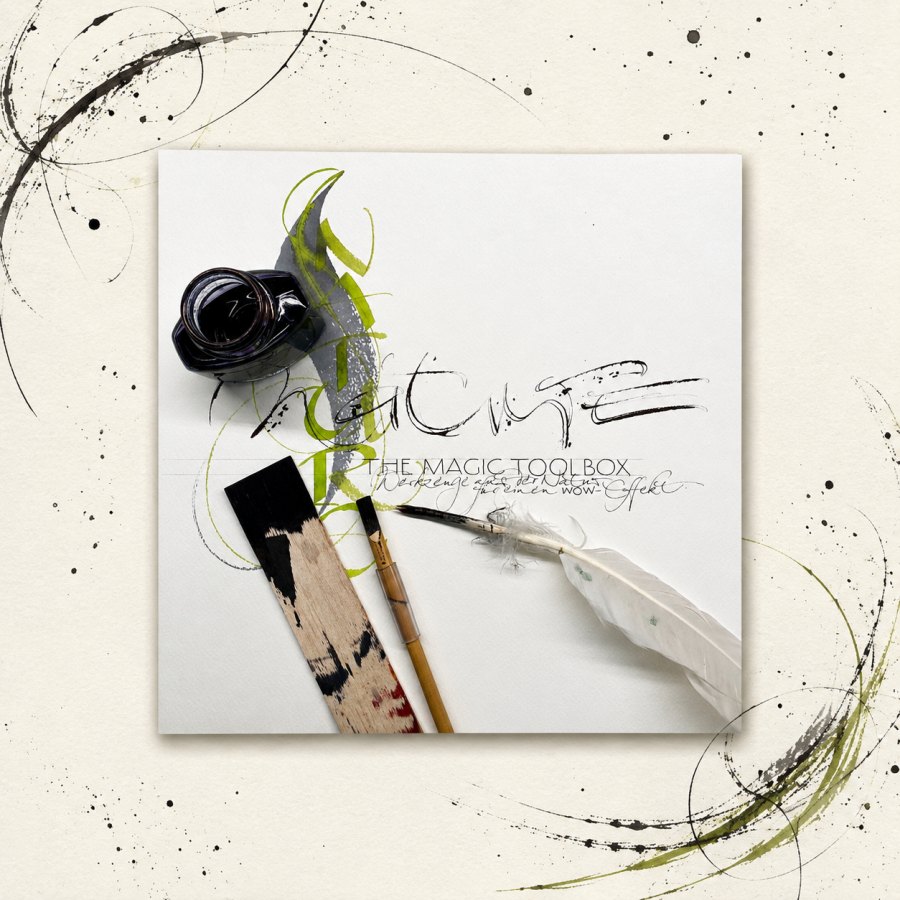
Gertrud und der Mut, es einfach zu machen
Gertrud Schetelig nennt sich selbst einen bunten Vogel. Als vielseitige Mixed-Media-Künstlerin verbindet sie Schrift mit Farben, Formen und Materialien zu lebendigen Kunstwerken.
Mit der INKademy einen außergewönlichen Weg eingeschlagen
Gertrud Schetelig nennt sich selbst einen bunten Vogel. Eine echte Mix-Media Künstlerin, denn Ihre Kunstwerke beinhalten nicht nur Schriften. Auch das Zeichnen nimmt einen großen Teil ein. Und genau so arbeitet sie auch. Farbig, neugierig, klar im Kopf und warm im Ton. Wer ihr zuhört, merkt schnell, dass hier nichts aufgesetzt ist.
Vom Sammelheft zur ersten eigenen KalligrafieWenn man Gertrud begegnet, hat man nicht das Gefühl, jemand sitzt auf einem fertigen Fundament. Eher so, als würde sie selbst, dieses ständig erweitern. Damit die weiteren Träume Platz für die Verwirklichung haben. Ihr Weg beginnt früh. Als Kind liebt sie alte Schriften und sammelt Vorlagen, die zeigen, wie man Fraktur oder andere historische Formen schreiben kann. Diese Hefte verschwinden irgendwann, ganz banal, weil jemand aufräumt und nicht ahnt, was da gerade weggeräumt wird. Es ist eine kleine Szene, aber sie passt sinnbildlich. Gertrud sucht jahrelang nach den Heften. Und irgendwann holt sie sich das, was fehlt, einfach zurück. Sie baut es neu auf. Mit Büchern, mit Übung, mit dem eigenen Kopf.
Dann kommt das Leben dazwischen. Ausbildung, Familie, Arbeit. Kalligrafie rutscht in den Hintergrund, bleibt aber als leiser Wunsch irgendwo im Kopf erhalten. Wie ein Notizzettel, ein Gedanke, der nicht weggeht. Und dann dieser Moment, den viele kennen und fast jeder zu lange verschiebt. Wann, wenn nicht jetzt. Rund um die Jahrtausendwende entstehen ihre ersten eigenen Arbeiten. Eine davon entsteht sogar, bevor sie überhaupt einen Kurs besucht hat. Das ist wichtig, weil es den Ton für alles setzt, was später kommt. Gertrud wartet nicht auf Erlaubnis. Sie probiert. Sie macht. Und sie schaut genau hin, was ein Wort braucht, damit es die passende Form bekommt. Bei ihr ist das nicht nur Lesbarkeit. Buchstaben dürfen bei ihr tanzen, lachen, trauern, sich umarmen. Sie sollen ausdrücken, was das Wort meint, nicht nur, was es sagt.
Dieses Denken macht ihre Arbeit sofort erkennbar. Schrift wird nicht dekoriert. Schrift wird gestaltet. Und Gestaltung ist bei Gertrud immer auch ein Weg vom Kopf übers Herz in die Hand. Erst wenn der Text bei ihr innerlich angekommen ist, darf er aufs Papier.
Lernen wie eine Handwerkerin, üben wie eine MusikerinMit vierzig schenkt sie sich ihren ersten Kurs. Und dabei bleibt es nicht. Sie reist, lernt, besucht Workshops, sammelt Wissen, schaut anderen über die Schulter und nimmt sich heraus, das Gelernte wieder zu drehen, bis es zu ihr passt. Sie beschreibt das selbst ganz offen. Lernen hört nicht auf. Und das spürt man in allem, was sie umsetzt.
Was besonders greifbar ist, ist ihre Beziehung zu Werkzeugen. Gertrud sagt sinngemäß, Kalligrafie lebe von Vielfalt. Klassische Schriften brauchen klassische Werkzeuge. Bandzugfeder, Spitzfeder, klare Regeln. Aber sobald es freier wird, wird auch das Werkzeug freier. Und dann schreibt sie eben nicht nur mit Feder. Sie schreibt mit Stöckchen, mit einem Strohhalm, mit Klavierfilz oder sogar mit einem Klarinettenmundstück. Nicht, weil es witzig klingt, sondern weil jedes Werkzeug eine andere Spur hinterlässt. Und jede Spur erzeugt ein anderes Gefühl beim Betrachten.
Damit ist sie nah an dem, was man in ihrer Arbeit immer wieder sieht. Linie ist nicht nur Linie. Linie ist Entscheidung. Mal streng und kantig, mal zart und kaum sichtbar. Mal kontrolliert, mal mit Schwung. Und Gertrud sagt selbst, sie habe lange sehr geplant gearbeitet. Layout, Elemente, alles sauber gesetzt. Heute liebt sie das Intuitive stärker. Dieses Umschalten ist kein Zufall. Es ist Erfahrung. Es ist das Vertrauen, dass nicht alles vorher festgezurrt werden muss, damit es trägt.
Auch beim Üben denkt sie nicht in schnellen Ergebnissen. Sie denkt in Wiederholung und Geduld. In einem Takt, der sich gut anfühlt. Sie spricht gern über Rhythmus, weil Rhythmus Druck rausnimmt. Wer schreibt, kennt das. Wenn die Hand hetzt, wird sie hart. Wenn der Takt ruhiger wird, wird die Linie ruhiger. Und plötzlich sieht die Schrift nach einem selbst aus, nur klarer. Gertrud bringt diesen Gedanken auch in ihre Handschriftarbeit. Nicht als strenges Programm, sondern als Einladung, mit Musik zu üben und die Hand wieder in einen gleichmäßigen Fluss zu bringen.
Einer ihrer liebsten Sätze zu Kursteilnehmern trifft genau ins Schwarze. Fünfmal schreiben ist erst der Anfang. Wer unzufrieden ist, soll nicht aufhören, sondern weitermachen. Zwanzigmal, dreißigmal. Bis die Hand versteht, was der Kopf will.
Rausgehen, Kurse geben, Strukturen bauen2007 geht sie mit ihrer Schrift zum Stadtmauerfest in Nördlingen. Der Impuls kommt vom jüngsten Sohn Michael. Und plötzlich steht sie da, mitten unter Menschen, mit einem Stand, mit geschriebenen Dingen, mit in der Öffentlichkeit. Gertrud beschreibt diesen Schritt als Mutprobe. Dieses Gefühl ist nachvollziehbar. Denn wer mit Schrift rausgeht, zeigt sich. Ohne Filter. Ohne Ausrede.
Zwei Jahre später kommt der nächste große Schritt. Ein eigenes Atelier in der Nördlinger Altstadt. Ein Raum, der nicht perfekt ist, eher dunkel und feucht, aber es ist ihr Raum. Sechs Jahre lang ist das ihr Ort, dort entstehen Arbeiten, dort entstehen Kurse, dort entsteht ein Kreis von Menschen, die bis heute bleibt. Und auch hier ist es wieder nicht die glatt polierte Gründergeschichte. Ihr erster Kurs entsteht nicht aus dem sicheren Gefühl, jetzt sei sie bereit. Er entsteht, weil jemand hartnäckig bleibt und ihr die Angst praktisch aus der Hand nimmt. Raum ist reserviert. Teilnehmer sind da. Jetzt machen.
Das ist ein Kern, der in ihrer ganzen Laufbahn wieder auftaucht. Gertrud wird nicht fertig, bevor sie beginnt. Sie beginnt, und sie wird unterwegs besser. Genau daraus wächst ihr Ruf. Nicht aus Lautstärke, sondern aus Verlässlichkeit. Aus der Fähigkeit, Dinge so zu erklären, dass andere wirklich weiterkommen. Aus dem Talent, Menschen mitzunehmen, statt sie klein aussehen zu lassen.
2015 zieht sie nach Reimlingen. Das Atelier wird Teil des Alltags. Ein großer Tisch, warme Räume, gemeinsames Arbeiten, gemeinsames Essen. Wer einmal so einen Kurs erlebt hat, versteht, warum Teilnehmer wiederkommen. Es ist nicht nur Inhalt. Es ist Atmosphäre. Es ist diese Mischung aus Konzentration und Leichtigkeit.
Dann kommt 2020. Lockdown. Von einem Tag auf den anderen sind Kurse und Jobs weg. Gertrud beschreibt das nicht dramatisch, aber klar. Plötzlich ist da Nichts. Und genau da passiert etwas Entscheidendes. Sie betritt die digitale Welt. Sie schaut, wie andere es machen, und dann macht sie es selbst. Nicht perfekt, aber echt. Onlinekurse entstehen. Videokurse entstehen. Und weil sie vielseitig aufgestellt ist, trägt sie diese Phase besser als manche, die sich nur auf einen einzigen Kanal verlassen haben.
Drei Jahre später gründet sie die INKademy. Eine Membership, die nicht nur aus einem Kursabend besteht, sondern aus einem Miteinander. Monatliche Einheiten, monatliche Treffen, eine Videothek. Content der immer weiter wächst. Das ist der Punkt, an dem ihr Weg nicht nur künstlerisch spannend ist, sondern auch unternehmerisch klug. Sie baut ein Modell, das weniger abhängig ist von Präsenzterminen, Wetter, Reisekilometern und dem nächsten freien Wochenende. Ein Teil der Arbeit entsteht einmal und bleibt nutzbar. Ein Teil lebt vom gemeinsamen Termin. Zusammen ergibt das Planbarkeit. Und ja, auch ein Einkommen, das wiederkehrt, statt jedes Mal bei Null zu starten.
Das ist der Teil, den viele unterschätzen. Gertrud hat nicht einfach nur ein Angebot. Sie hat eine Struktur gebaut. Diese Struktur ist vor allem persönlich. Sie ist Community. Sie ist das Gefühl, nicht allein am Tisch zu sitzen.
Zu dieser Verantwortung passt auch ihr Engagement bei Ars Scribendi. Sie ist Kuratoriumsmitglied und arbeitet im Verein auch ganz praktisch mit, dort, wo es oft keiner sieht. An der Website, am Newsletter, an den Fäden im Hintergrund. Das ist kein Glamour. Das ist Dienst an der Szene. Und es zeigt, wie sehr ihr Schrift mehr bedeutet als das eigene Portfolio.
Mit Sympathie und Authentizität zum ErfolgAm Ende bleibt ein Eindruck, der sich nicht künstlich herstellen lässt. Gertrud ist sympathisch, weil sie echt ist. Weil sie das Spielerische zulässt und trotzdem ernst nimmt, was sie tut. Weil sie nicht so gern das Offensichtliche mag, das laut schreit, sondern lieber das Subtile, das auf den zweiten und dritten Blick mehr erzählt. Und weil sie ihre Liebe zur Schrift nicht nur zeigt, sondern weitergibt. Als Wegbegleiterin, die Menschen ermutigt, den eigenen Ausdruck zu finden.